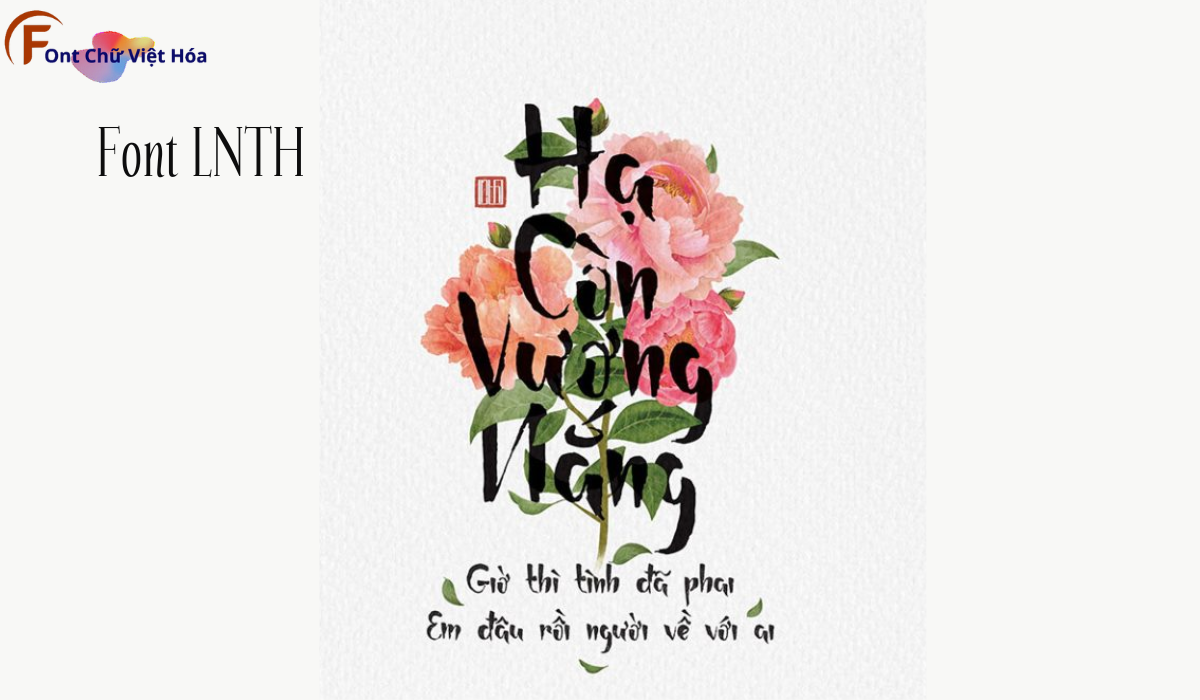
Font LNTH Watermark Việt Hóa
Font LNTH Watermark
Bộ Font: LNTH
Phân loại: Cá tính
Kiểu chữ: Không chân
Độ dày: Regular
Font LNTH Watermark
Font LNTH Watermark Việt Hóa là một font chữ hiện đại, thuộc bộ LNTH, với thiết kế đơn giản và tinh tế. Phong cách của font này phù hợp với các dự án cần sự hiện đại và thanh lịch, như logo, tiêu đề, hoặc bảng hiệu. Font LNTH Watermark Việt Hóa mang đến sự hiện đại và dễ nhận diện, ứng dụng trong các lĩnh vực sáng tạo. Đặc điểm hình dạng của font bao gồm các đường nét gọn gàng và tinh tế, giúp tăng tính thẩm mỹ và sự chú ý. Việc Việt hóa font giúp người dùng dễ dàng sử dụng trong các thiết kế tiếng Việt, mang lại sự tiện lợi và linh hoạt.
Font LNTH Watermark việt hóa